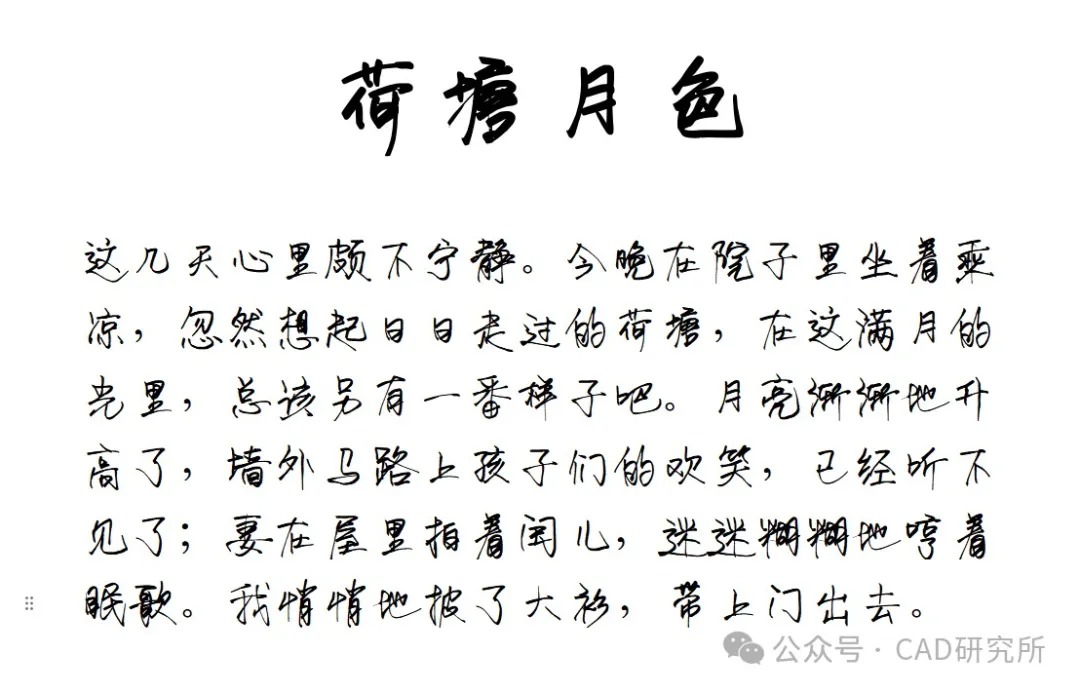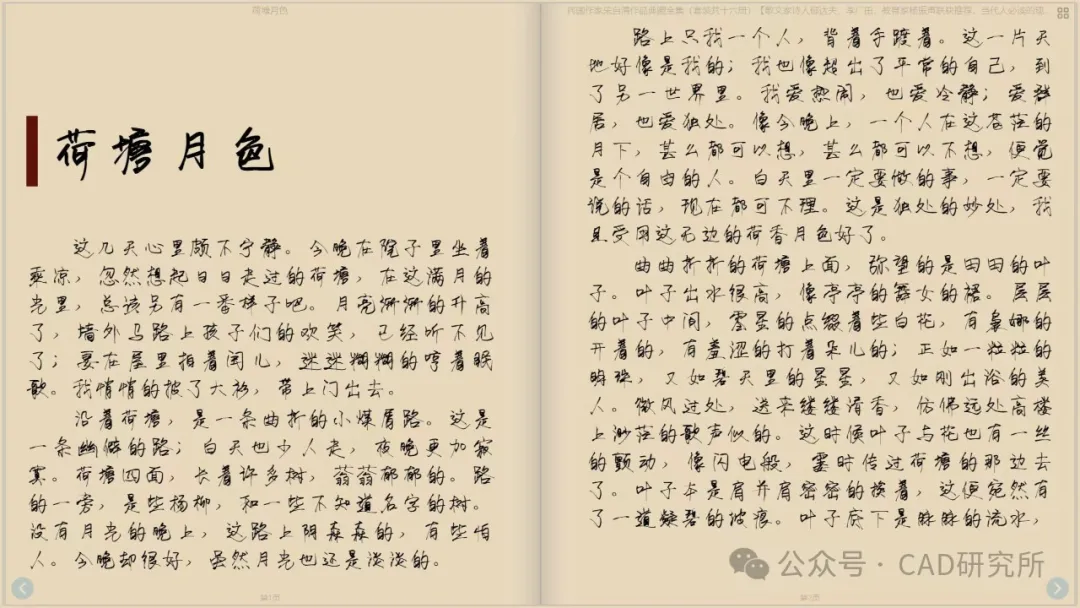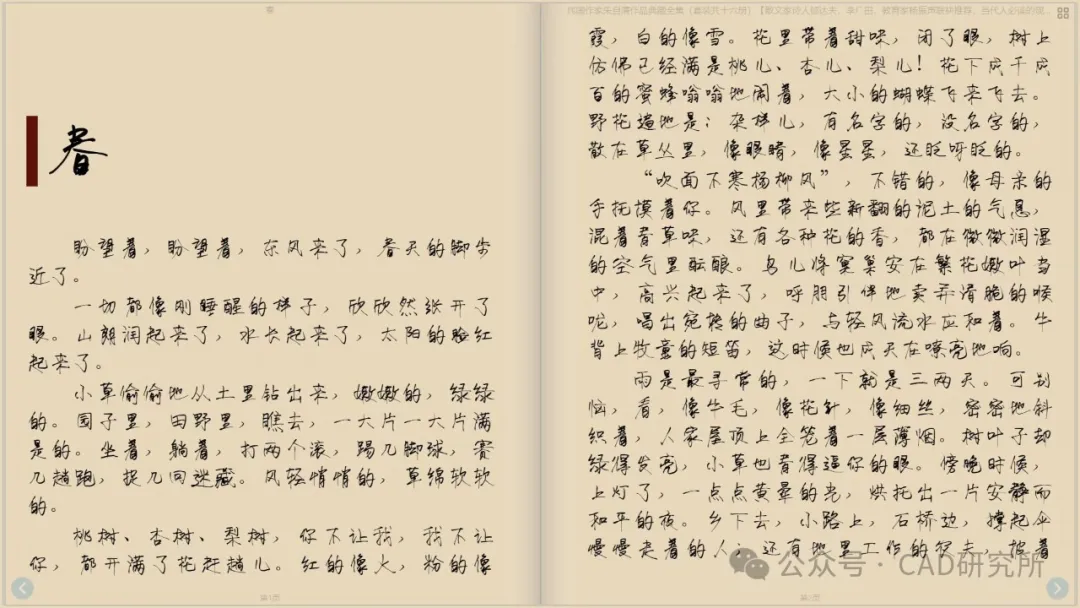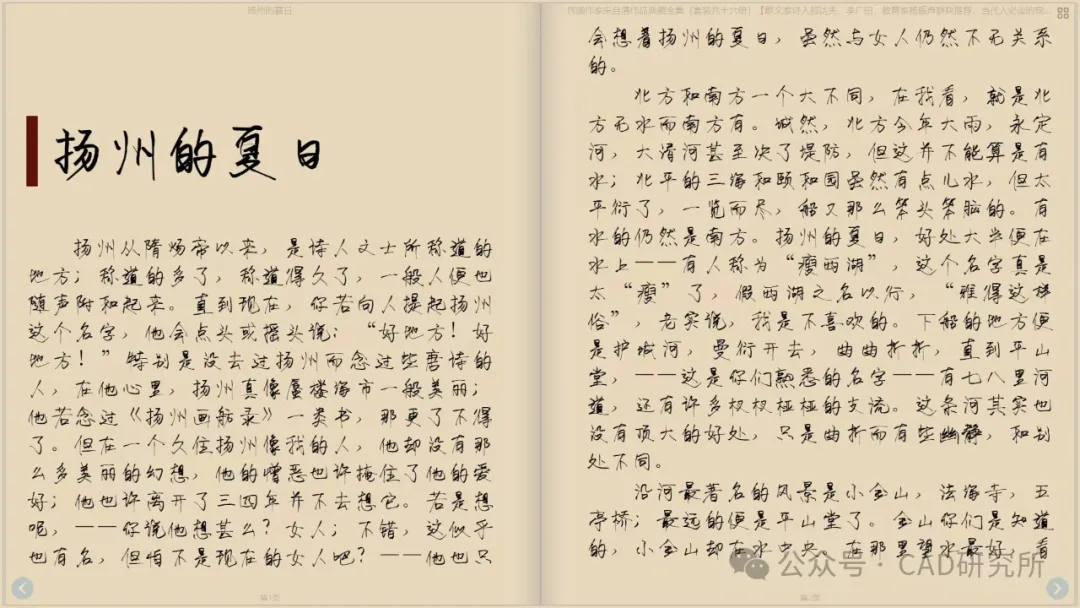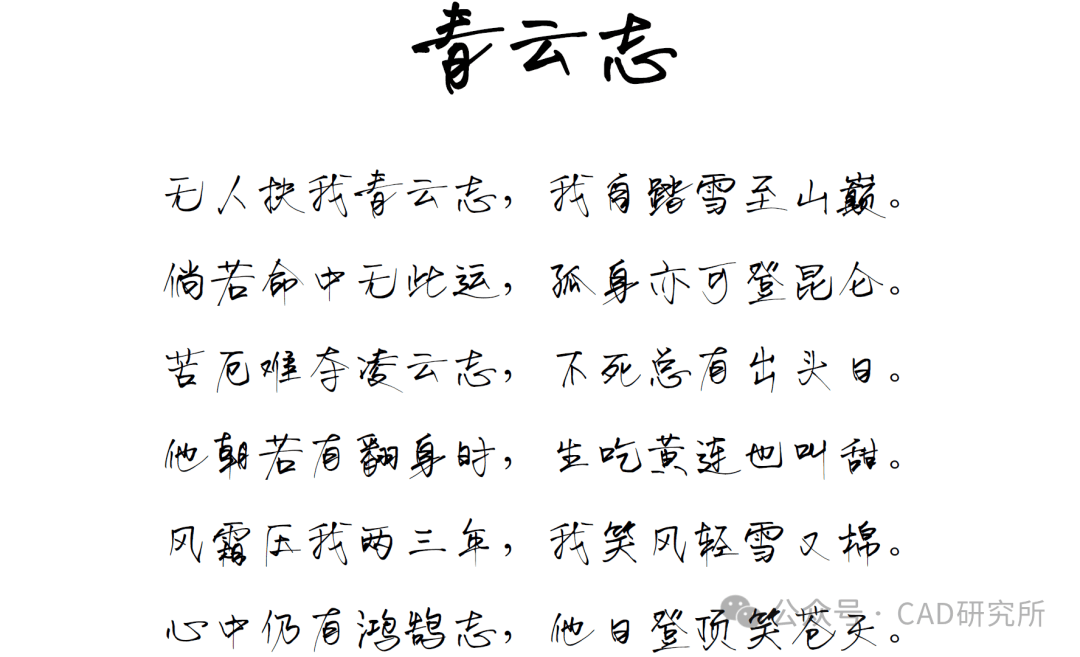
《荷塘月色手写体》字体简介
话不多说,先看效果
在电子书软件中预览
创作动机
作为一名深化设计师,我在工作中常常需要手绘线条,同时手写文字以辅助表达。然而,有时候文字较多,逐个书写不仅麻烦,也可能影响美观。因此,我决定设计一款手写字体,以后便能一劳永逸,免去手写的烦恼。
名称由来
最初,我为这款字体取名“豆角豆角手写体”,因为我的女儿小名叫“豆角”。这也算是送给她的一份礼物。当她长大后,能够使用这款字体时,她所打的每一段话,仿佛都是爸爸亲手写给她的,相信她一定会喜欢。
写字其实有些枯燥,所以在创作初期,我并不是按照字典从头到尾开始写,而是挑选一些我喜欢的文章来进行书写,顺便测试排版效果。其中,有一篇恰好是朱自清的《荷塘月色》。开篇的第一句话:“这几天心里颇不宁静”,深深触动了我。作为一个设计师,反复修改作品确实让人心情不宁静。读到朱自清悄悄披上大衫走出门外的情景时,我想,1927年的朱自清或许也是个白天上班后感到疲惫,晚上外出散心的人吧。与文中那种既有淡淡的喜悦,又有淡淡的哀愁的复杂情感,我不禁感同身受。作为同为父亲的人,我倍感共鸣。
文字流淌了百年,但依然为无数人带来心灵的慰藉。于是,我决定将这款字体命名为“荷塘月色”,因为我开始创作这款字体时,正是在一个盛夏的夜晚。希望大家在使用这款字体时,能感受到它名称所蕴含的意境,体会到内心的宁静。
这款字体是我从夏天的晚上写到冬天的晚上完成的。大多数时间我是在夜晚进行创作,因为工作日白天需要工作,而周末则陪伴女儿。总的来说,历时六个月,我认为测试版已经完成。当前发布的“荷塘月色手写体”仍为“预览测试版”,在未来两年里,我将继续优化与完善这款字体,同时着手设计另一款字体。大家如有反馈意见,欢迎给我留言。